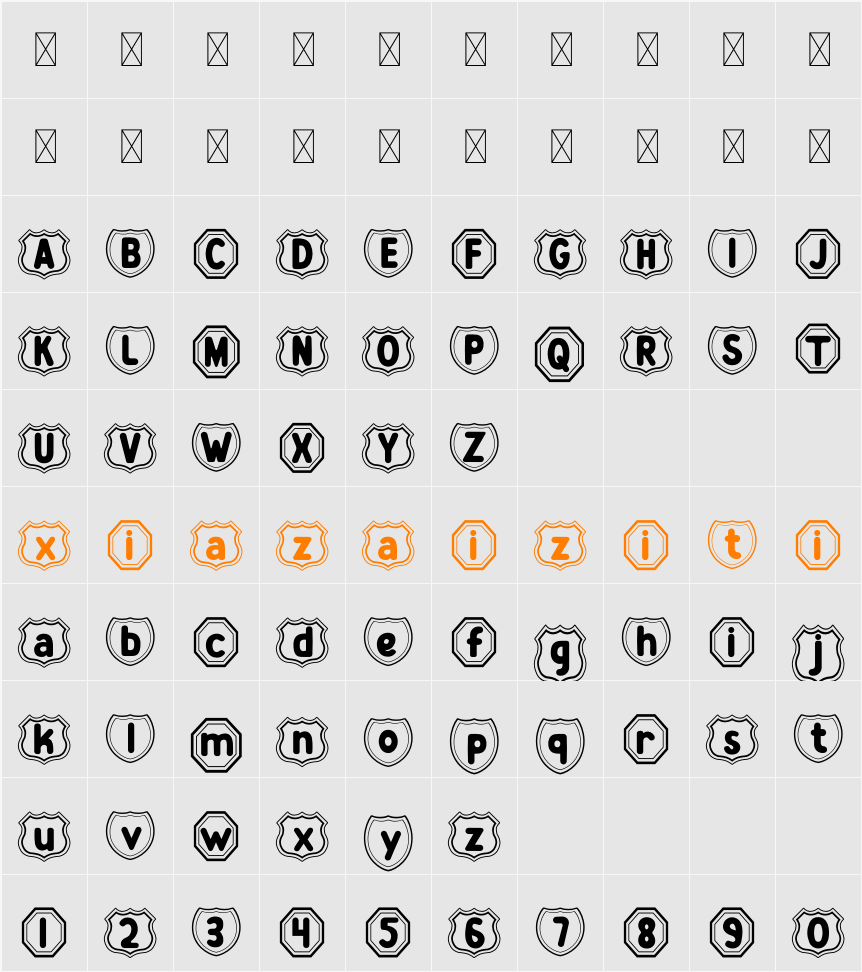
Zany Route Badge
Zany Route Badge,这款字体结构工整、笔画清晰,兼顾美观与易读性,适用于标题、正文、海报、包装、LOGO 等多种场景。字形优雅稳定,风格百搭耐看,适配日常排版与创意设计,让文字呈现更舒适、更具质感。Zany Route Badge一笔一画,皆是细节,以均衡的比例、流畅的线条打造舒适视觉体验,字形端正大气,风格简约现代。无论是商业设计、品牌宣传还是日常排版,都能轻松驾驭,让文字更有格调与力量。Zany Route Badge字体下载。